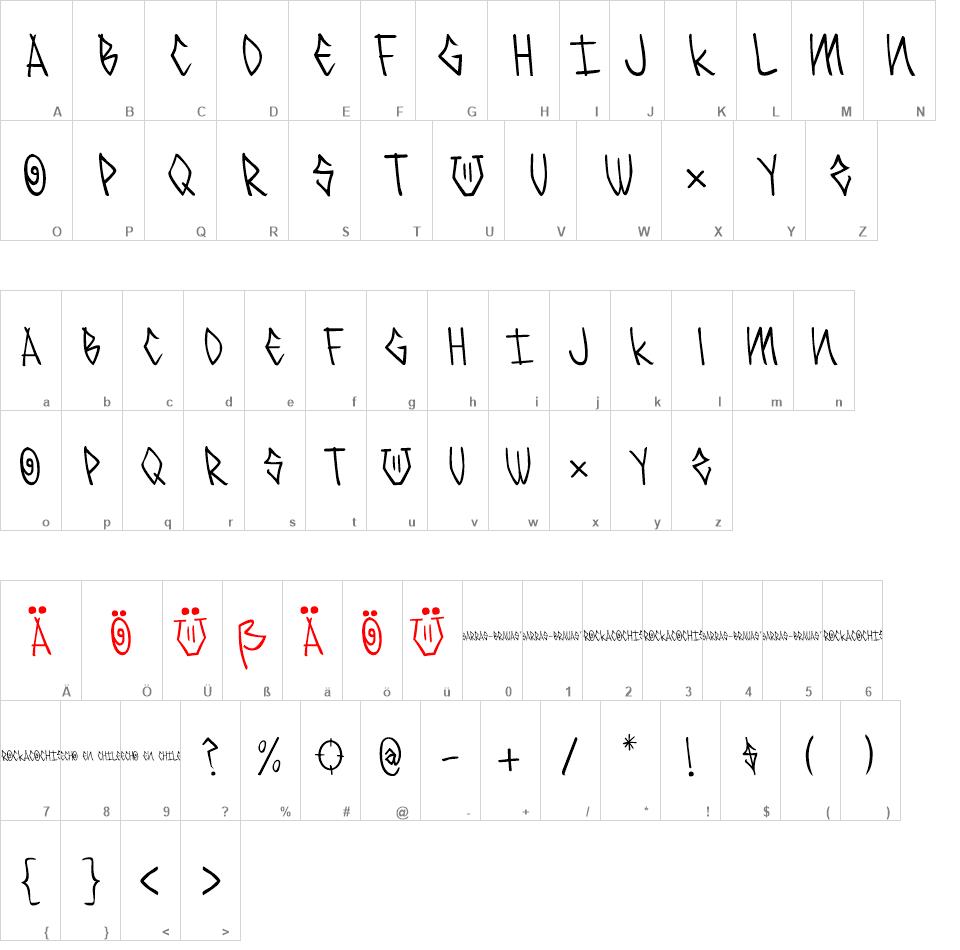
Barras-Bravas
Barras-Bravas  font
Barras-Bravas font
"BARRAS-BRAVAS"
BASADO EN LA FORMA DE ESCRIBIR DE BARRISTAS CHILENOS
EN LA CUAL, LA PUEDES ENCONTRAR DE CUALQUIER PARTE DE CHILE, YA MEER UN BAÑO PUBLICO, EN EL BUS, DE EL COLEGIO, ECT ..
VERTRETER DER BASICAMENTE ALGO DE NOSOTROS, QUE TIENE QUE VER CON NUESTRA SOCIEDAD Y NUNCA ES MOSTRADA.